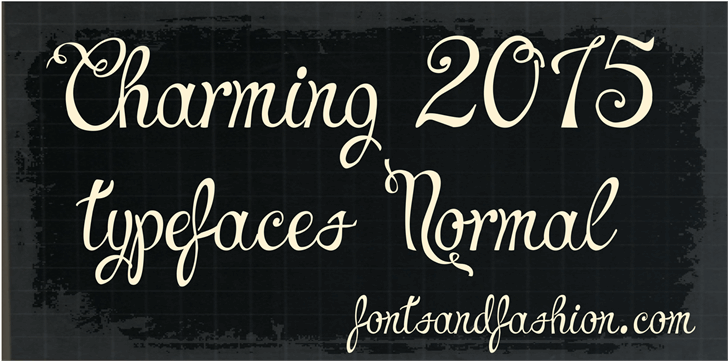
A fonte “Charming Normal” é uma criação do designer Hamilton lançada em 2014. Esta fonte tem um charme próprio que se assemelha a escrita à mão, proporcionando um toque natural e sofisticado aos projetos digitais. Com linhas levementes e formas suaves, ela é ideal para criar textos emotivos e criativos, seja em cartazes de moda ou no design editorial. Sua elegância permite que você personalize qualquer projeto, tornando-a uma escolha popular entre designers profissionais e amadores que buscam um toque pessoal em suas criações digitais. Através da “Charming Normal”, Hamilton trouxe a arte subtil do traçado à experiência digital, oferecendo aos criativos um meio de expressar seus sentimentos através dos caracteres.